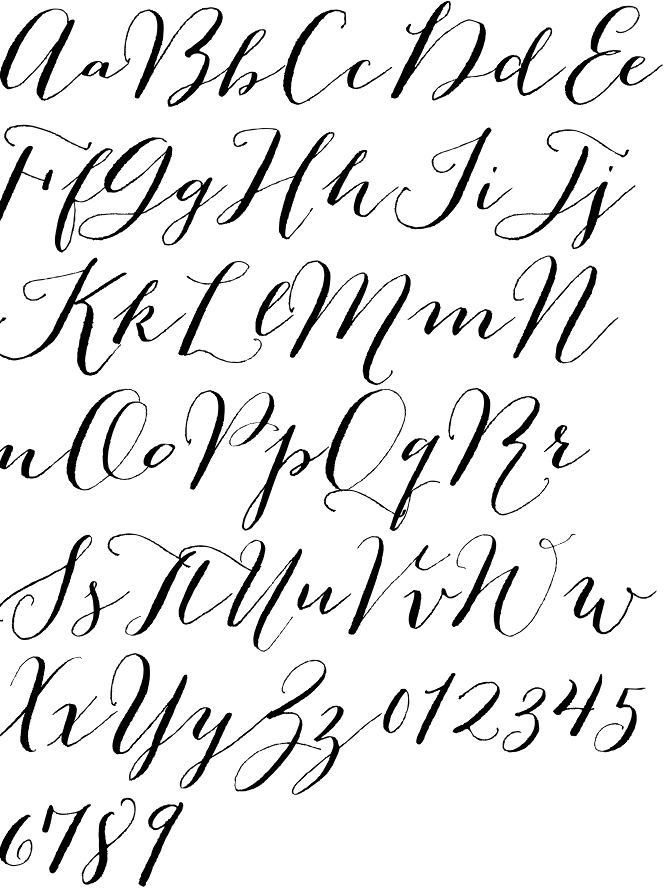
60 лучших бесплатных шрифтов для дизайнеров 2022
A шрифт сценария как видно из названия, это шрифт, который выглядит как рукописный сценарий и стили каллиграфического письма.
Выбор правильного шрифта сценария для вашего дизайна может быть важным решением, которое влияет на общую визуальную привлекательность вашего веб-сайта или индивидуального дизайна.
Правильный рукописный шрифт может кардинально изменить вашу творческую работу, и для этой цели доступны различные привлекательные бесплатные шрифты.
Это список некоторых из самые привлекательные бесплатные шрифты Script которые были разработаны дизайнерами для дизайнеров, чтобы эффективно удовлетворить потребность в универсальных и бесплатных шрифтах из первых рук.
Вы можете использовать любой из этих лучшие бесплатные скриптовые шрифты для вашего следующего проекта и выделите свой дизайн.
Все эти шрифты можно использовать в полиграфии, онлайн-брендировании, графическое проектирование и любые другие цели для создания потрясающих визуальных дизайнов.
Вот полный список лучших бесплатных шрифтов для дизайнеров:
Алекс Браш
Это красиво плавный скрипт кисти, разработанный TypeSETit. Благодаря своей элегантной каллиграфии он обеспечивает читаемость, которой нет в других рукописных шрифтах. Этот каллиграфический шрифт отлично подходит для формальных целей.
АрхипелагArkipelago — красивый рукописный шрифт, который можно использовать бесплатно. Загрузите шрифт и без колебаний начните использовать его в своем проекте.
Шрифт действительно выглядит стильно и может стать отличным вариантом для любого проекта, связанного с рекламой, дизайна баннеров, поздравительных открыток или даже логотипа.
БродлиBroadley был разработан Хендри Джуандой, причудливый нарисованный от руки шрифт, который сделает ваш дизайн привлекательным.
Этот шрифт хорош для любого баннера, дизайна рекламы, контента в социальных сетях.
Вы можете оживить его хорошей цветовой комбинацией, чтобы шрифт выглядел еще более привлекательным.
PacificoЭтот связный рукописный шрифт, разработанный Верноном Адамсом, напомнит вам шрифты, которые использовались в первой половине 20-го века в США. Этот стиль шрифта с ретро-привлекательностью выполнен в одном стиле и содержит более 200 глифов.
Pacifico — отличный скриптовый шрифт для создания логотипов, поздравительных автомобилей или любого другого баннера.
Бариста Скрипт Бесплатный ШрифтДля создания этих букв скручен красивый связанный рукописный шрифт, похожий на веревку.
Если вы ищете современный рукописный шрифт, Barista — хороший вариант для вас. Этот тонкий рукописный шрифт — отличный вариант для контента, связанного с рестораном, дизайна рекламных щитов, дизайна карт или даже для дизайна логотипа.
СалмелаSalmela — красивый шрифт для каллиграфии от руки от лаборатории Genesis. Этот плавный сценарий можно использовать для создания свадебных приглашений, фирменных бланков, логотипов, подписей и многого другого.
Большие VibesGreat Vibe — это элегантный рукописный шрифт, разработанный TyprSETit. Great Vibes содержит более 400 глифов и выполнен в едином стиле. Буква разработана таким образом, что они идеально соединяются друг с другом, независимо от того, в каком порядке вы их расположите.
ОмарШрифт от Impallari Type, Lobster разработан таким образом, что каждая буква связана с другой, независимо от того, в какие комбинации букв вы их вставляете. Этот креативный шрифт содержит более 300 глифов и выполнен в едином стиле.
Сетта сценарийЕсли у вас есть бренд одежды, этот Setta Script идеально вам подойдет.
Этот шрифт лучше всего подходит для дизайна, который нуждается в естественном и индивидуальном подходе. Шрифт можно настроить и использовать в соответствии с вашими требованиями, и вы даже можете включить элегантное сообщение в свой дизайн, используя setta.
Каушанский сценарийKaushan Script — это современный и элегантный шрифт. Этот современный рукописный шрифт имеет буквы каллиграфического стиля и в целом создает уникальный вид. Шрифт содержит более 400 глифов и имеет единый стиль.
Гиллиган Шаттер МонолайнGilligan Shutter Monoline, один из самых красивых и качественных рукописных шрифтов в этой коллекции, выглядит потрясающе.
Вы можете использовать этот фирменный шрифт для любого проекта, такого как логотип, реклама, поздравительные открытки, проекты, связанные со свадьбой.
Демонстрация шрифта Portobello RoadЕсли вы хотите, чтобы ваш дизайн был утонченным, где стильный рукописный шрифт сопровождается классическим шрифтом с засечками, этот шрифт будет лучшим для вас.
Это очень универсальный шрифт, который охватывает различные языки и является пробной версией трио шрифтов от UnioCS.
текст, который довольно популярен в Instagram, Twitter, Facebook и многих других социальных сетях.